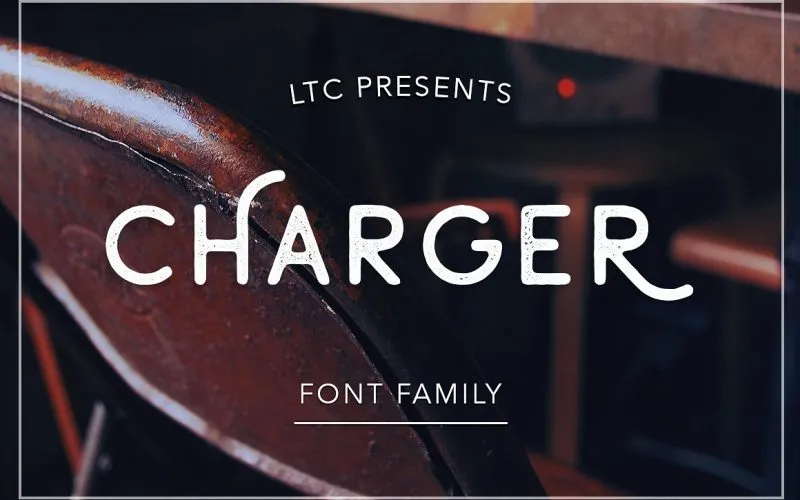
A fonte ‘Charger Typeface’ é uma elegante tipo aberto sans-serif condensada que traz belas curvas e padrões agradáveis para as fontes condensadas tradicionais. É perfeitamente adequada para criar roupas, como camisetas, casacos, sudários; materiais de sinalização; cartões de negócios; marcas e marcas de negócio. Embora seja uma fonte sans-serif, que apresenta um aspecto mais suave e flexível, isso lhe dá muitas opções para o seu projeto. Este tipo aberto é ideal para qualquer trabalho que exija condensação, como materiais de moda ou design de identidade visual.